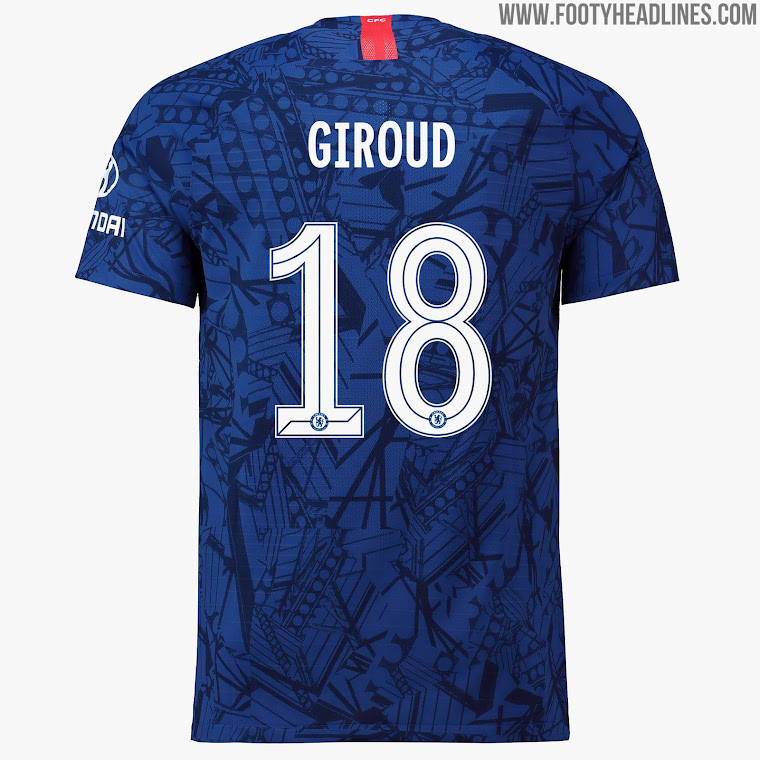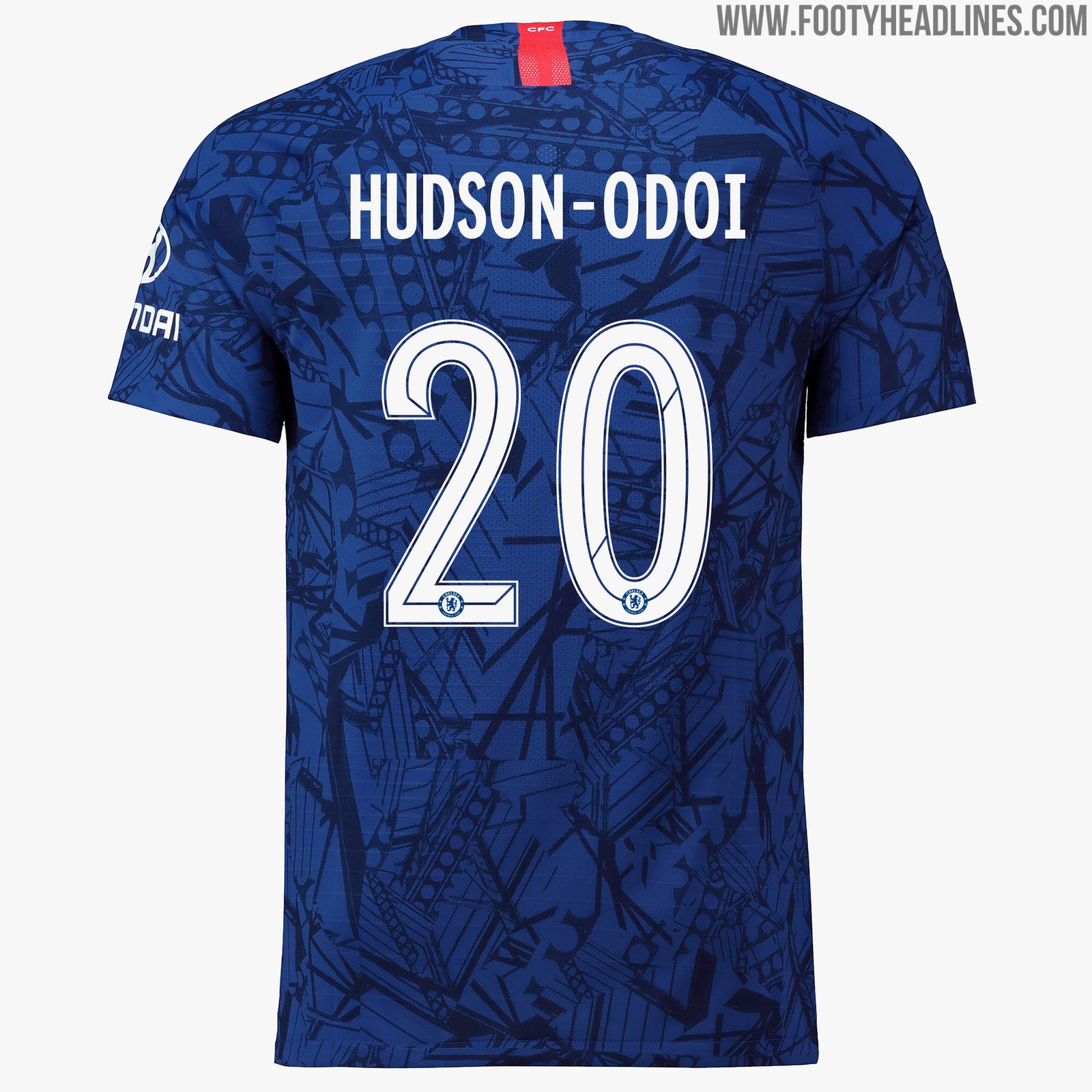
Neues Chelsea 19-20 Trikot - Pokal-Schriftart Enthüllt
Aktualisiert mit einem Bild aller Nummern und Buchstaben der neuen Chelsea 2019-2020 Pokal-Schriftart. Wir haben auch das Bild von Hazards Trikot nach seinem Transfer zu Real Madrid entfernt.
Chelsea 2019-2020 Pokal-Schriftart
Chelsea hat eine völlig neue Schriftart auf den Markt gebracht, die mit dem 2019-2020 Heimtrikot verwendet wird. Während sich die Premier-League-Schriftart in der nächsten Saison nicht ändern wird, werden wir die neue Chelsea-Schriftart bei allen Pokalwettbewerben im In- und Ausland in Aktion sehen.
Im Vergleich zu den eher einfachen Bemühungen der letzten Saison hat die neue Chelsea 2019-20 Schriftart ein viel einzigartigeres Aussehen, zum Teil aufgrund der dünnen Linien, die in der Mitte und an den Seiten der Formen hinzugefügt wurden. Am unteren Ende jeder Ziffer befindet sich ein kleines einfarbiges Blues-Wappen.